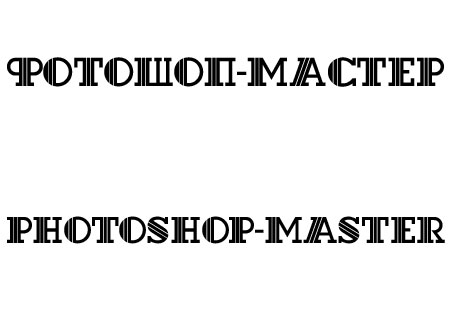
Дополнения Шрифты Татьяна Гапонова 18 июля 2009 Шрифт - DEXTORC Шрифт с рассечёнными буквами. Скачать Шрифт - DEXTORC
нет русского
поддерживает или нет?
насчет русского - действительно не поддерживает((
тоже(
У меня этот шрифт русский язык не поддерживает :(